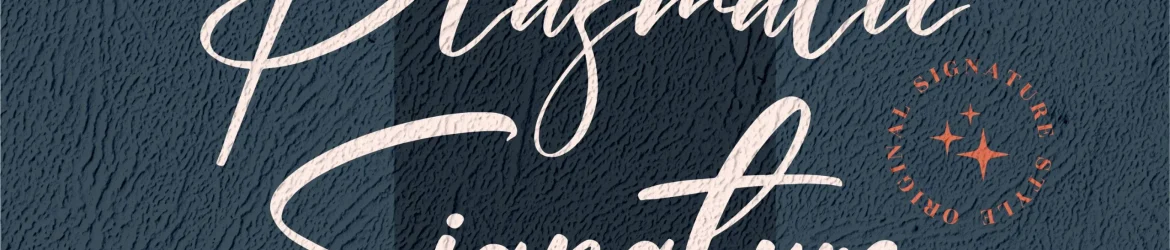
Plasmatic Signature Font – Download Grátis
A Plasmatic Signature Font oferece uma experiência visual única que combina modernidade com um toque elegante na escrita de mão. Este é um font premium, perfeito para uma variedade de projetos, desde logomarcas e identidades corporativas até designs de porta-malas e embalagens de produtos. Sujeitada a tarefas variadas como ilustrações, etiquetas ou até mesmo em impressões digitais, esta font é um complemento perfeito para qualquer projeto que exige uma assinatura de luxo. Proporcionando uma escolha sofisticada e autêntica, a Plasmatic Signature Font não apenas adiciona um toque especial aos seus projetos, mas também as torna únicas. Suas linhas suaves e nuances em tons variados criam texturas que transmitem confiabilidade e elegância, garantindo sempre uma assinatura de qualidade para seu trabalho. Seja você um designer gráfico ou um artesão, a Plasmatic Signature Font é a escolha perfeita para dar um toque final diferenciado a seus projetos.